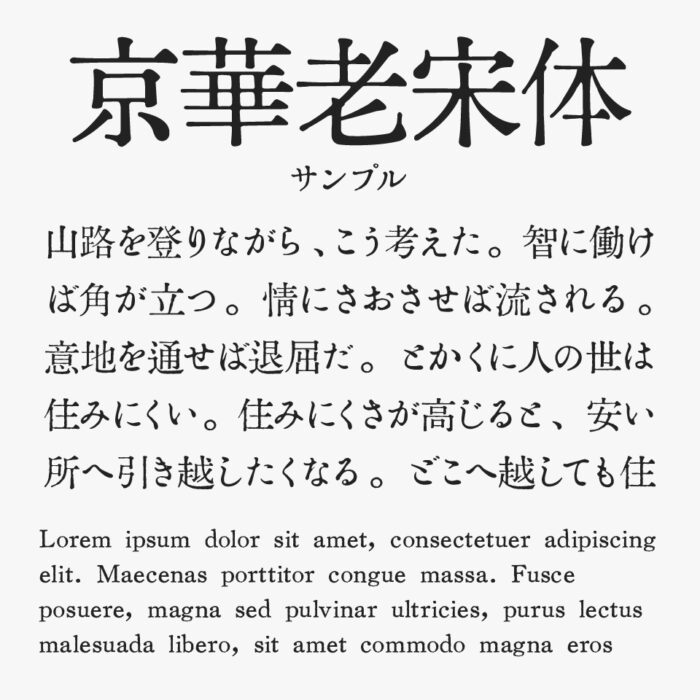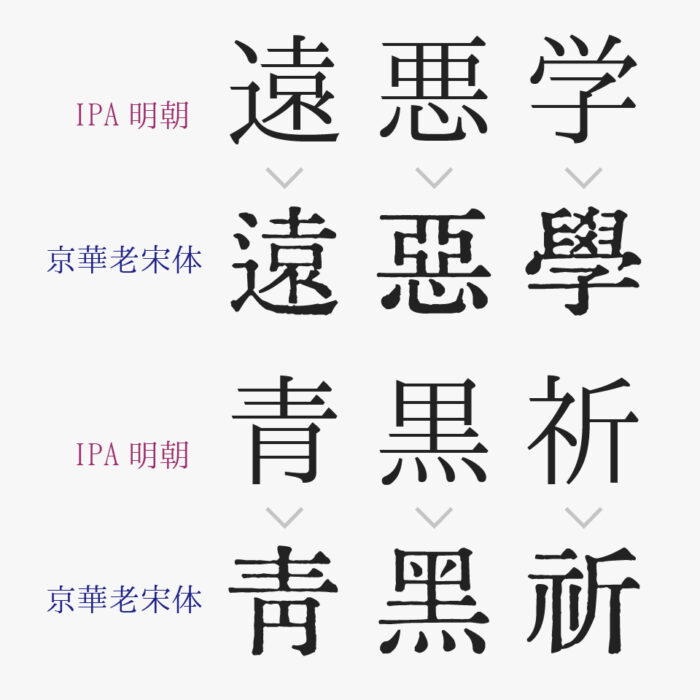
京華老宋体(KingHwa OldSong)フォントは、中国のタイプデザイナーであるテリー・ワンが、築地明朝体から着想を得て制作した明朝体フォントです。
筆遣いの名残を感じさせる繊細な払いが随所に見られ、文字全体にはやわらかな温もりが漂います。読みやすさと品格を兼ね備えた、知的で格調高い雰囲気が魅力です。
さらに、活版印刷を思わせるレトロな風合いも印象的に仕上がっています。インクのにじみや墨溜まりといった細やかに再現されており、紙の質感やアナログな空気感を感じられるフォントとなっています。
旧字や正字にも対応しているので、大正レトロなどの古風な雰囲気づくりをしたい場面にぴったりの明朝体フォントです。
中国の簡体字をベースに設計されているため、一部の漢字は日本で一般的に使用されている字体と異なる場合があります。日本語の文章に使用する際には、字形に違和感が出る可能性があるため、ご注意ください。